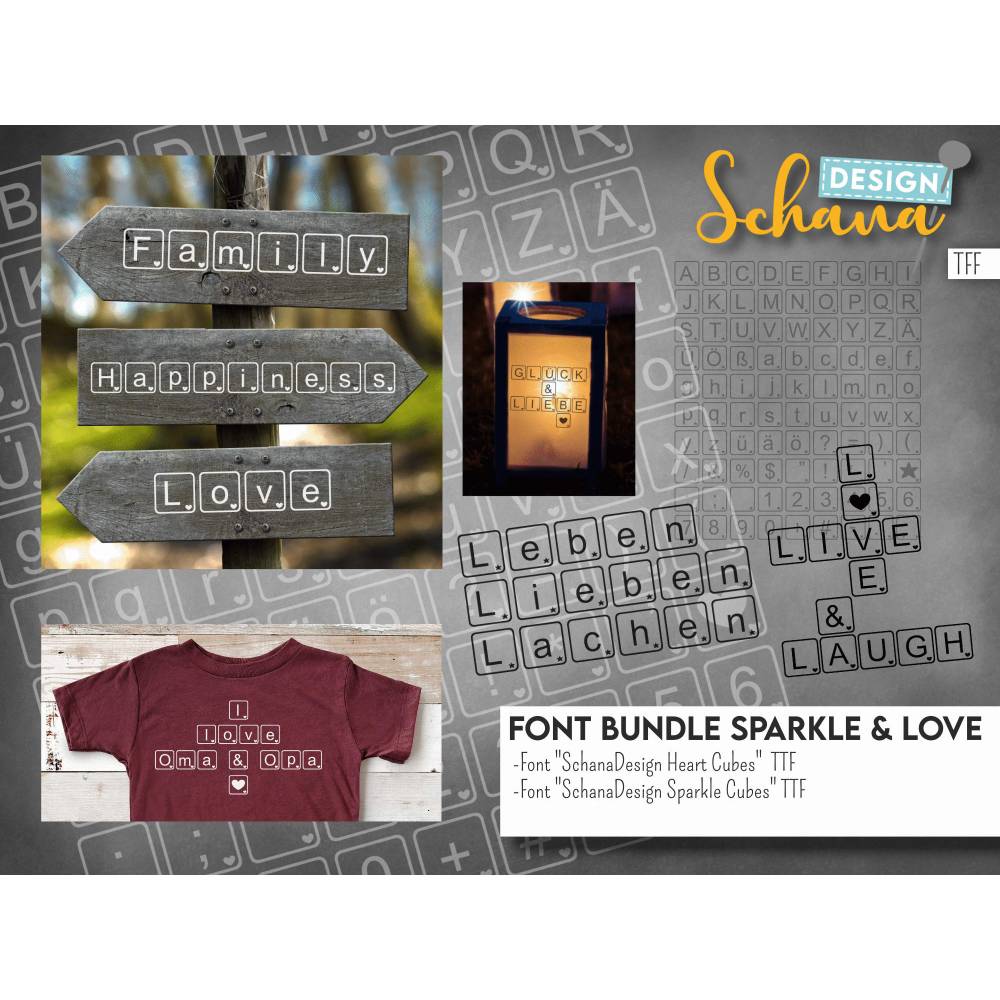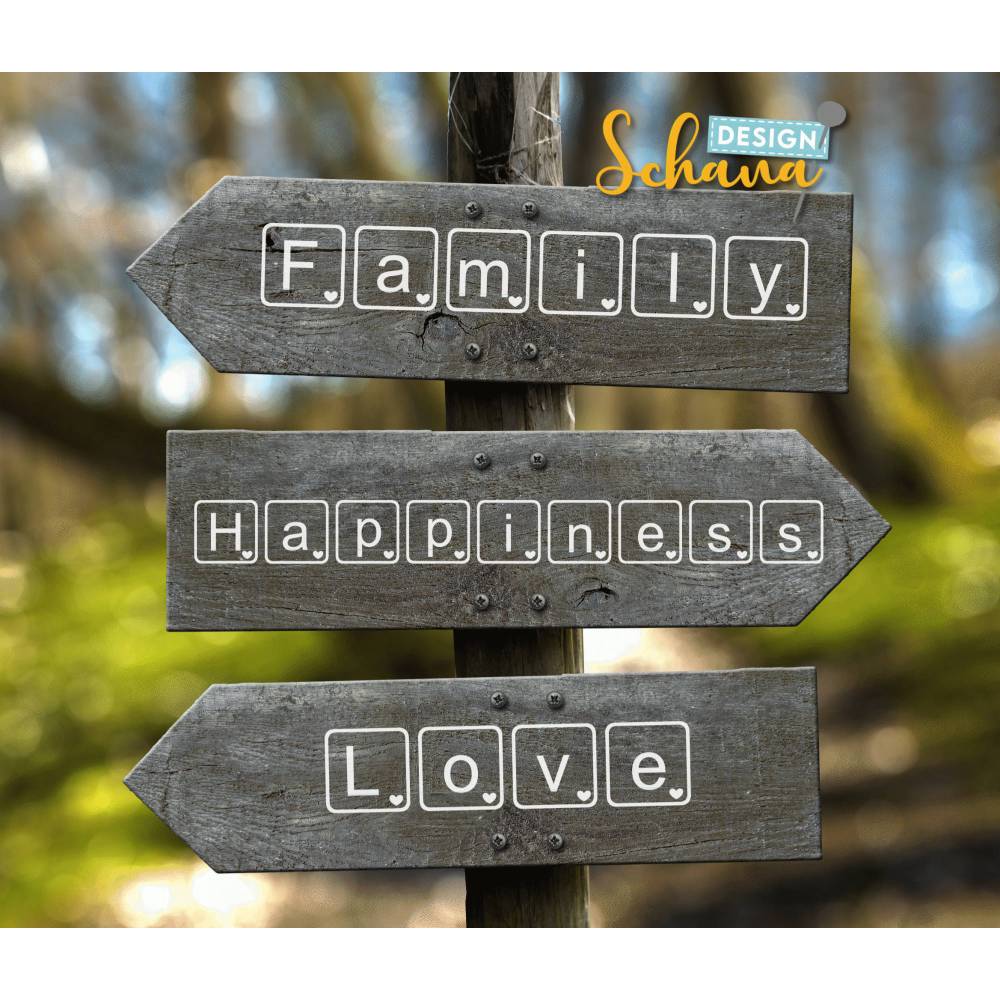
Schriftart Set 2 TTF Font Buchstabenwürfel mit Herz und mit Stern moderne Schriftart im Kreuzworträtsel Design Plottbar
Wunderschöne, verspielte und auch edel einsetzbare Schriftart. Hier erhälst du 2 Fonts im Sparset.
Ob zum Verschönern deines Bullet Journals oder beim Scrapbooking, du willst einen Liebesbrief schreiben oder eine andere Datei verzieren, auch zum Plotten und Lasercut eignet sich diese Schrift. Sie ist vielfältig einsetzbar und wartet nur auf ihren Einsatz.
-SchanaDesign Heart Cubes
-SchanaDesign Sparkle Cubes